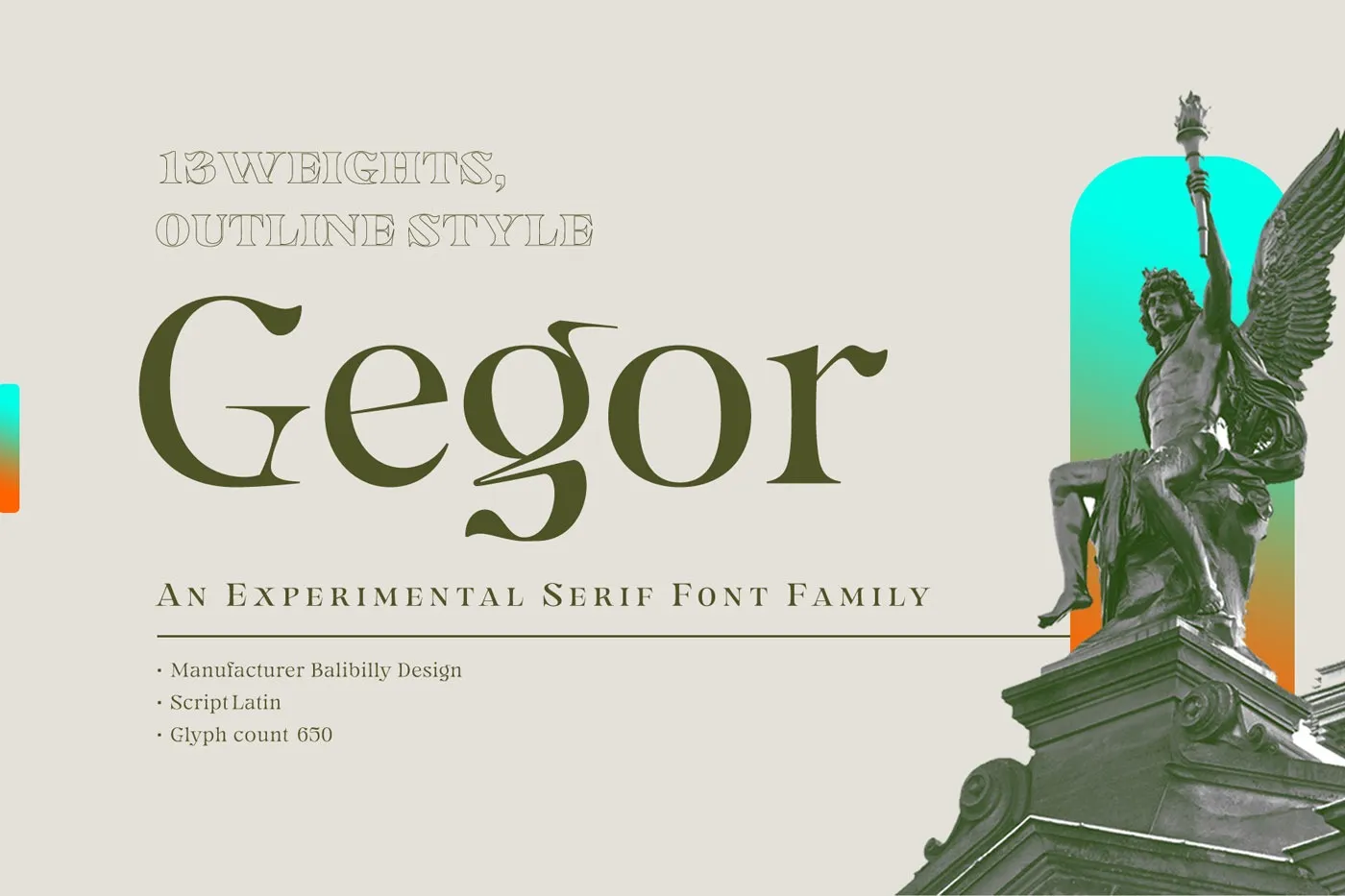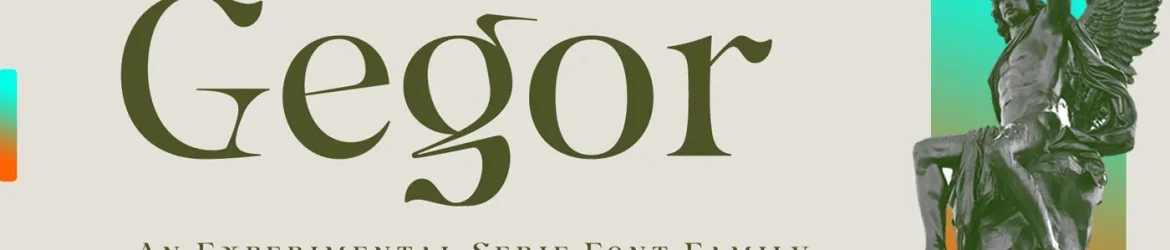
Gegor Serif Font é uma elegante tipografia serif que surge dos traços do caracter “r”. Criada pela BalibillyDesign, essa fonte traz formas afiadas e perfeitas para designs modernos com sabor retro. Seus caracteres são inspirados na forma angular do “r”, o qual se influencia mutuamente ao longo de sua desenvoltura. As formas simplistas nas costas dos caracteres ganham um toque pontilhado, especialmente em pesos mais grossos, enquanto as linhas curvas nas versões mais finas têm um grande impacto sobre outros caracteres. A forma única do “r” no Gegor Serif Font nos leva a uma evolução que resulta num harmonia distintiva e sofisticada, perfeita para ambientes de exibição. Seja você designer ou criador de materiais gráficos, esta fonte é uma ótima escolha para quem busca um toque retro moderno.